어쩌면 격동고딕 그 자체? 폰트 디자이너 장수영
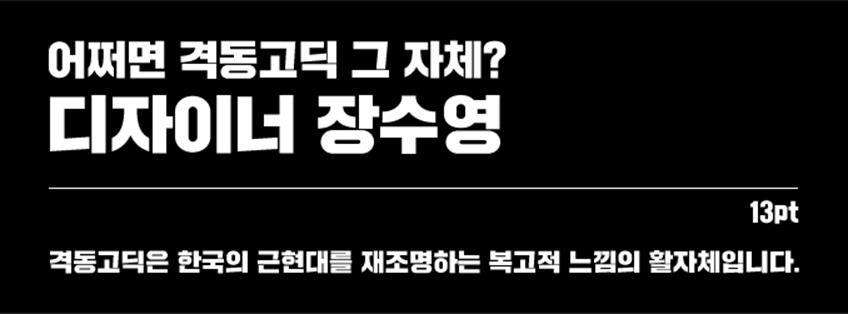
폰트를 가만히 바라보고 있으면 폰트 디자이너의 에너지나 성향, 감성을 느낄 수 있을 때가 있다.하지만 이번 ‘격동고딕’만큼 폰트와 디자이너가 잘 어울리는 경우는 처음이었다! 우리가 매일 들여다보는 스마트폰 화면이나 TV 속에서, 지나가다 한 번쯤 봤을 법한 바로 그 폰트! ‘격동고딕’의 디자이너 장수영과 시크한 ‘단문단답’을 나눠봤다. 거, 일도 바쁜데 짧은 호흡으로 갑시다!
SBS 매직아이 포스터(좌)와 카카오톡 스티콘(우)에 사용된 격동고딕
격동고딕이 공중파 방송(SBS 매직아이)과 팬시상품(바른생활시리즈)을 통해 활발히 소개되고 있다.디자이너로서 기분이 어떤가?
아직 부족하다. 더 활발해져야 한다!
격동고딕을 아는 지인도 많을 것 같다. 주변 반응은 어떤가?
격동고딕이 제작된 지 3년이 지났다. 처음에는 ‘멋지다, 좋다’던 반응들이 나중에는 ‘언제 출시되냐’로,지금은 ‘나오긴 하냐’로 바뀌었다. 내부 사정으로 인해 출시가 다소 늦은 감이 없지 않지만 지금이라도 출시되어 다행이다.
격동고딕이 사용된 카카오톡 스티콘 ‘바른생활 시리즈’는 꾸준히 최다 판매 순위를 유지하고 있다.본인의 폰트가 들어간 스티콘, 사용하고 있는가?
지난번 회사에서 판매 1위 기념으로 직원들에게 스티콘을 뿌렸는데, 휴대폰이 박살 나는 바람에 몇 번 못 써봤다. 개인적으로 이모티콘을 혐오하는 성격이라 있어도 자주 사용하지 않는다.
제작에 있어 중요하게 생각한 점은 무엇인가?
현대적인 재해석, 진지함이 묻어 날 것. 이렇게 두 가지 방향을 잡고 작업을 진행했다. 결국에는 현재 사용되어야 하기 때문이고, 당시의 정치적 상황이 모티브가 된 서체이기 때문이다. 형태적인 재미나 감성을 자극하는 인상보다는 묵직하고 무던한 인상을 주고 싶었다.
격동고딕 제작과정 중 기억에 남는 에피소드가 있다면?
회사에서 ‘살았던’ 기억뿐이다. 회사와 학교를 병행하던 때였고, 졸업전시 준비까지 동시에 하느라 회사에서 거의 먹고 잤다. 덕분에 인턴기간 내내 꾀죄죄함을 유지했다.
격동고딕이 처음 제작된 건 3년 전이다. 그 때와 비교했을 때 지금 폰트에 변화가 있다면?
글자 구조 자체가 크게 바뀌진 않았다. 굵기나 비례 등이 조금씩 수정되었으며, 형태적으로는 곡선이 가장 많이 수정되었다. 얼마 전 납품 건이 있어서 1년여만에 원도파일을 열어봤는데 당시에 ‘이 정도면 괜찮네’라고 생각했던 곡선이 지금 보니 너무 이상했다. 곡선의 맺음 부분이 수직으로 끊어지는 컨셉이라 원래 핸들링이 좀 어려운 설계이긴 한데, ‘내가 이랬었나?’ 싶을 정도로 괴상한 형태였다. 하지만 ‘그만큼 내가 늘었구나’라고 생각하며 기쁜 마음으로 수정했다.
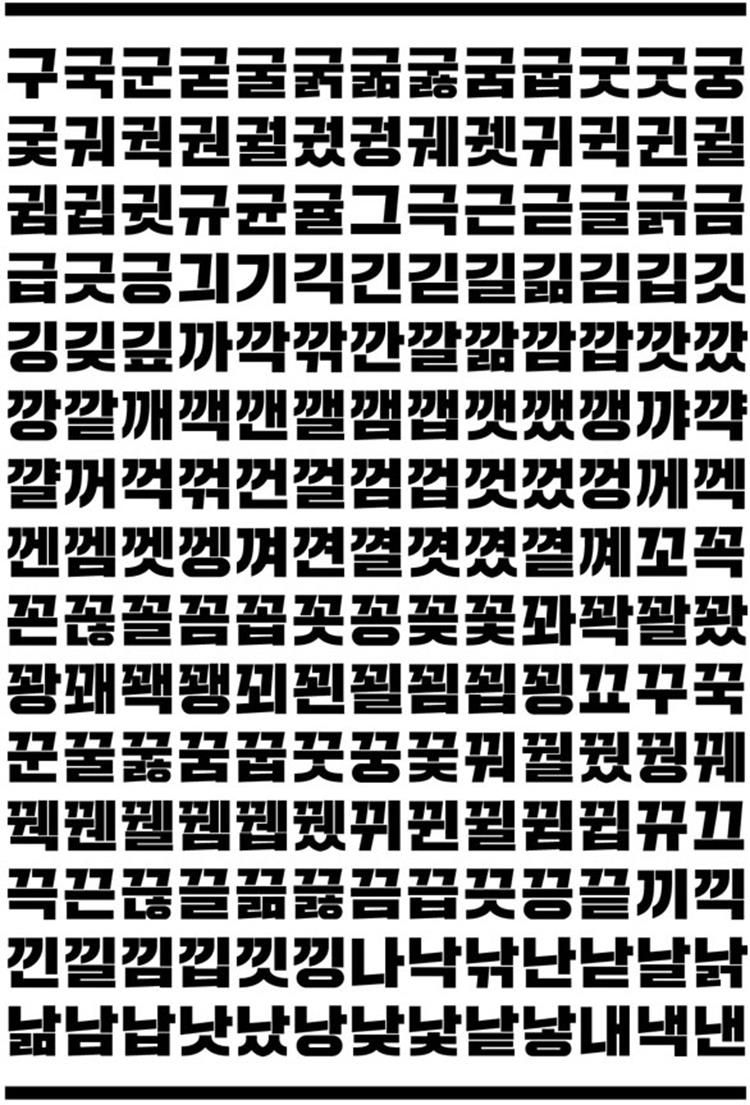
격동고딕 낱글자들의 모습
격동고딕이 판매될 때 폰트의 배경이 된 70, 80년대 물가에 맞춰 판매하고 싶은 바람이 있다고 했다.
작업은 혼자 했지만 회사선배들 도움도 받았고, 소유권은 회사에 있기 때문에 그 부분에 대해서는 체념했다. 그냥 비싸게 많이 팔려서 인센티브나 왕창 받았으면 좋겠다.
격동고딕의 가장 큰 매력이나 인기 비결은 무엇이라고 생각하나? 아쉬운 점이 있다면?
인기가 전제가 되어야 한다는 점에서 ‘인기 비결’이란 단어가 적절한지는 잘 모르겠지만, 사용자 입장에서는 눈에 띄는 제목용 서체에 대한 요구가 오래 전부터 있어왔다. 현재 개인작가나 폰트회사에서 출시되는 서체들만 봐도 캐릭터 있는 서체들이 많지 않나. 이 서체는 그런 요구에 의해 만들어졌고, 격동고딕 또한 그에 편승한 것이라 생각한다. 다만 좀 일찍 출시되었으면 하는 아쉬움뿐.
격동고딕을 사용자들이 어떻게 써주면 좋을까?
어떻게 사용할지는 사용자들 마음이라고 생각한다. 감자를 사서 튀겨먹을 수도 있고, 볶아먹을 수도 있고, 삶아먹을 수도 있고, 카레 만드는데 들어갈 수도 있듯이 어떤 식으로 뭘 해먹을지는 당사자 마음 아닐까? 다만 그들의 요리가 훨씬 맛있어질 수 있는 곳에 원하는 맛이 날 수 있도록 쓰였으면 좋겠다.
3년 전 졸업작품 인터뷰 댓글을 보면 폰트의 인기를 예감한 분들이 많았다. 격동고딕을 아끼는 분들께 전하고 싶은 말이 있다면?
요즘은 어떻게 지내나?
일이 말 그대로 일이 돼 버린 지 4년째에 접어들면서 몸도 마음도 썩어가고 있다. 일 안에서, 작업 안에서, 술 안에서(?) 글자 자체의 즐거움을 찾으려 발버둥치고 있다.
예전에 ‘디자인이라는 마을에서 쌀 농사를 시작한 새내기 농부’로 비유되었다. 개인적으로나 작업적으로나 지금은 어느 정도 내공이 쌓였을 것 같은데?
벼농사로 비유하자면 이제 모내기가 막 끝난 단계 정도 될까. 워낙 서체 쪽이 ‘레벨 업’하기 힘든 바닥이라.
어릴 때는 어떤 아이였나? 어떻게 서체 디자인을 시작하게 되었는가?
어릴 때 삶의 모토는 ‘재미’였다. 재미가 있냐, 없냐가 삶의 판단기준이자 의사결정의 기준이었다.나이를 먹으면서 재미로만 세상을 살아갈 수 없다는 것을 깨닫게 되었고, 먹고 살기 위해 재미들을 하나씩 접었다. 그리고 몇 안 남은 재미 중 하나가 지금 내가 하고 있는 이 일이다. 평생의 업만큼은 재미없이 하고 싶지 않았다. 그림이 좋아서 시각디자인과로 진학했고, 거기서 배운 것들 안에서 내가 제일 잘 할 수 있고 제일 재미있는 직업을 택했다. 그렇게 시작했고 여기까지 왔다. 사실 얼마 오진 않았다.
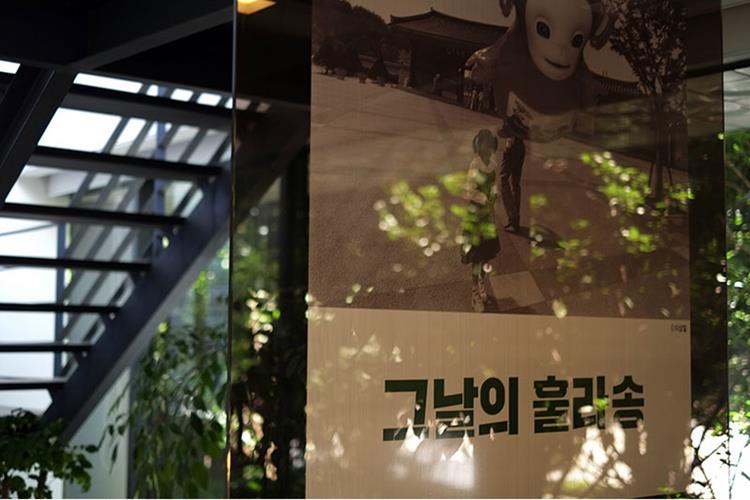
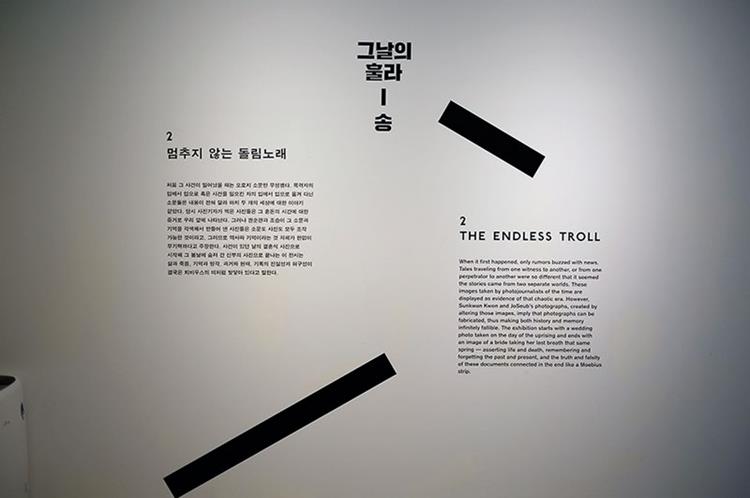
작년에 열린 5.18 33주년 기념전시 <그날의 훌라송>. 시대를 그대로 담은 격동고딕이 사용되었다. (출처-고은사진미술관)
새로운 것으로 인해 소멸되거나 퇴보한 아날로그적 느낌을 좋아한다고 언급했었다. 특별한 이유가 있나?
선천적인 기계 치다. 그래서 디지털과는 거리가 멀다. 책으로 보면 술술 읽히는 것도 e-book으로는 몇 줄만 읽어도 멀미가 난다. 아직도 가끔 음반을 사러 오프라인 레코드샵에 간다.
산돌커뮤니케이션에는 어떻게 입사하게 되었나?
대학생 때 막연히 글꼴디자인을 해야겠다고 마음먹고서 필묵 아트센터에서 한글디자인 수업을 받았다. 그때 강사님이 당시 산돌의 수석디자이너였던 이호(현 닥터폰트 대표) 대표님이셨다. 내가 마음에 드셨는지 수업이 끝나고 몇 개월 뒤 산돌에서 인턴을 뽑는다고 연락이 와서 지원했고, 그 연으로 산돌에 다니고 있다.
입사해서 처음 맡은 일은 무엇이었나?
기아자동차 브랜드서체 다국어 파생이었던 것 같다. 선배들이 시키는 대로 뭔가를 만들었다는 추상적인 기억만 남아있다.
입사 후 겪은 재미있는 에피소드가 있다면?
첫인상이 상당히 좋지 않은 외모의 소유자이다. 찢어진 눈에 늘어진 수염, 껄렁한 걸음걸이에 차가운 경상도 말투까지. 첫인상을 뒤엎을 만한 반전매력 발산을 위해 노력하지만 아직도 선배들은 술 마실 때면 얘기한다. ‘내가 너보다 빨리 입사해서, 내가 너의 선배라서 다행’이라고.
맞다. 격동고딕과 비슷하게 디자이너 자체도 강렬한 인상을 지니고 있는 것 같다.
몇 번 안 갔는데도 대학로 가게 사장님들이 먼저 말 걸어주시는 거 보면 그런 것 같긴 하다.
인턴이었던 3년 전 본인처럼, 사내에 후배도 생겼을 것이다. 후배 디자이너를 보면 어떤 생각이 드는가?
그들이 20대라는 것에 한없이 부러움을 느낀다.
격동고딕이 사용된 NIKE CUP 247 포스터 (출처-안그라픽스)
요즘 가장 관심을 두고 있는 것은?
외국에 나가서 공부하는 꿈을 꾼다. 시간 날 때마다 서체를 가르치는 학교들을 검색하며 커리큘럼을 훑어본다. 돈이 없어서 꿈만 꾸고 있다. 그리고 영어도 못한다. 결론은 못 갈듯.
폰트 디자이너가 되지 않았다면, 지금 무엇을 하고 있을까?
디자인과 출신에 딱히 직업은 없는 일용직 노동자? 하고 싶은 일이 없으면 굳이 할 필요가 없다는 주의기 때문에 하루하루 밥 벌어먹으며, 하고 싶은 일을 찾고 있을 듯 하다.
진심으로 자유분방함이 느껴진다. 좌우명은 무엇인가?
‘굵고 길게’. 욕심이 많은 편이다. 기회비용 따위는 생각하고 싶지 않다.
폰트 디자이너로서 앞으로의 각오가 궁금하다.
죽기 전에 우리나라 역사에 길이 남을 만한 본문용 활자 한 번 만들어보고 싶다. 아마 한글 폰트를 디자인 하시는 분들 모두의 목표가 아닐까?
작업 시 가장 신경 쓰는 부분이나 원칙이 있다면?
‘한글 타이포그라피의 한 획을 그으리라’는 비장한 각오로 작업을 시작하지만, 하나의 폰트가 만들어졌을 때 절대 깨지지 말아야 할 원칙은 결국 ‘오탈자’다. 글자는 ‘시각적인 예술’이기 이전에’기능하는 정보’이기 때문에 ‘가’라는 글자가 ‘가’로 읽히지 않는다면, 아무리 아름다운 디자인을 해도 글자로서의 가치가 없다. 그래서 조판테스트나 검수 볼 때가 제일 긴장된다. 근데 얼마 전에 실수를 하나 했다. 내가 담당이었던 일을 이어 받은 선배님이 발견해서 알려 주시더라. 그래서 이제부턴 그냥 긴장이 아니라 ‘극도로’ 긴장하기로 했다.
충무로 인쇄 골목에서 오래된 간판 사진을 찍으며 격동고딕에 대한 영감을 받았다고 했다. 영감을 위해 요즘 하고 있는 것이 있나?
특별히 하는 건 없다. 간판, 잡지, 사인 등 주변에 있는 글자들을 평소 유심히 보는 편이다.
그렇다면 서체 제작의 매력은 무엇이라고 생각하는가?
서체가 갖는 지속성이 좋다. 쉽게 만들어지지 않고 쉽게 사라지지도 않는다. 묵직하고 진정성 있는 느낌이랄까? 개인적으로는 상업미술 안에서 그나마 본질에 대해 생각해볼 수 있는 직업군 중 하나가 아닐까 한다.
격동고딕 외 가장 기억에 남는 프로젝트가 있다면?
평소 즐겨 쓰는 폰트가 있다면?
일을 시작하면서부터 편집은 거의 손을 놓다시피 한 상태이다. 즐겨 쓰는 게 아니라, 사용을 거의 못해봤다. 이 점이 서체 디자이너들이 갖는 딜레마이기도 한 것 같다. 그 외에 관심 가진 디자이너가 있다면 ‘사이러스 하이스미스’다. 스케치를 바탕으로 한 색다른 조형들이 재미있게 느껴진다. 이 사람 작업을 보면서 나도 RISD에 가서 공부해보고 싶다는 꿈을 잠시나마 꿔본 적이 있다. 학비보고 헉 소리 내며 바로 접었지만.
사이러스 하이스미스의 작품
좋아하는 서체 디자이너나 롤모델이 있다면 소개해 달라.
헤르만 자프, 메튜 카터, 에릭 슈피커만 등 환갑이 넘도록 글자 가지고 씨름하시는 모든 디자이너들을 존경한다. 개인적으로 롤모델로 삼은 사람은 없다. 새로운 유형의 디자이너가 되고 싶다.
장수영 폰트 디자이너